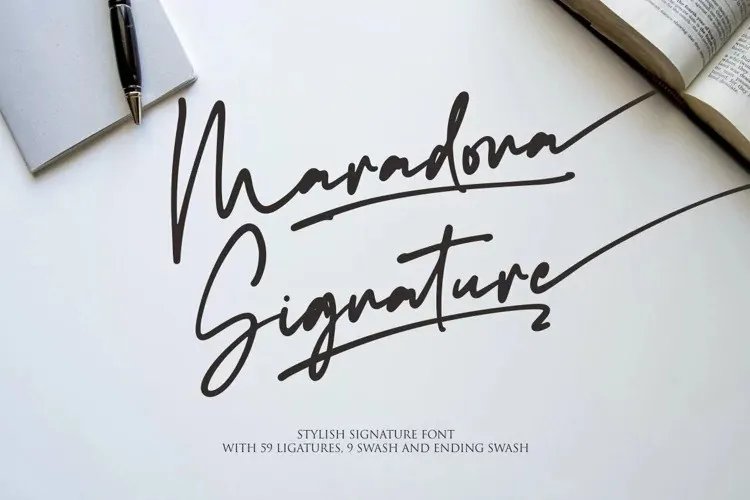
A fonte Maradona Signature é uma escrita elegante e encantadora que se destaca por seus 59 ligaturas e 9 swashes no final das linhas, criando um aspecto sofisticado e único. Este design foi concebido por NJ Studio, uma equipe de estilistas fontes apaixonados pela arte da escrita. A Maradona Signature é perfeita para quem busca dar um toque especial a seus projetos digitais, elevando-os ao próximo nível. Com sua natureza única e elegante, essa fonte irá impressionar os amantes de letras que valorizam tanto o estilo quanto a funcionalidade, tornando-a uma escolha ótima para designers gráficos e apaixonados por fontes.